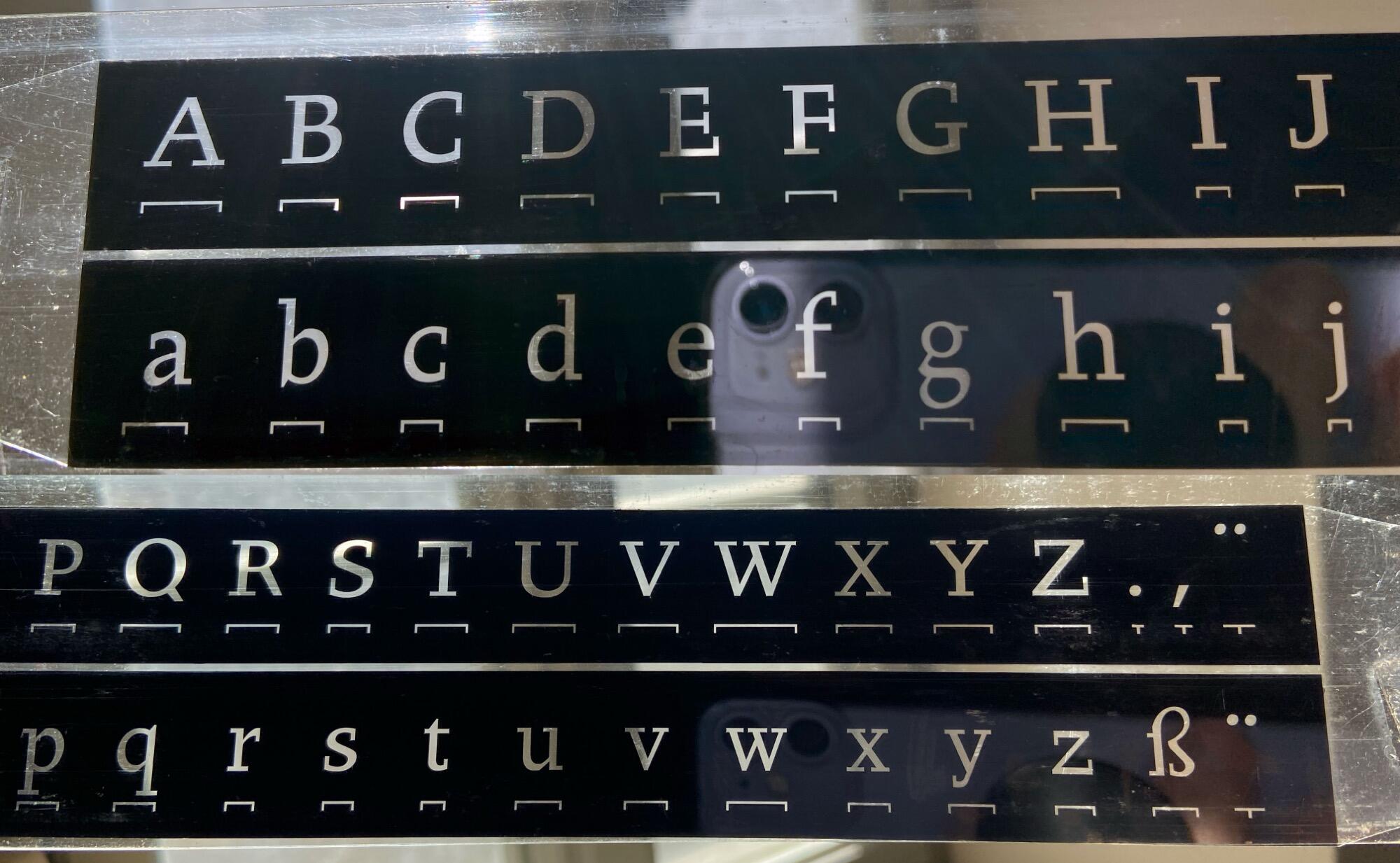
Unbekannte Willberg-Fotosatzschrift
Eine Fotosatzschrift aus dem Nachlass von Hans Peter Willberg, die augenscheinlich selbst zwischen zwei Plastikstreifen geklebt wurde.
Erkennt sie jemand? War es eine Kopie einer frei verkäufliche Schrift? Es kann natürlich auch eine Hausschrift oder gar eigene Schrift aus seiner Arbeit sein.
Ich erinnere mich dunkel, dass die »Bilderbücher der Sechs« irgend so eine Sonderauflagenvertriebsgeschichte der Kinderbuchverlage Bertelsmann, Stalling, Betz, Maier (Ravensburger), Herder (?) und Oetinger gewesen sein müsste. Hilft das?